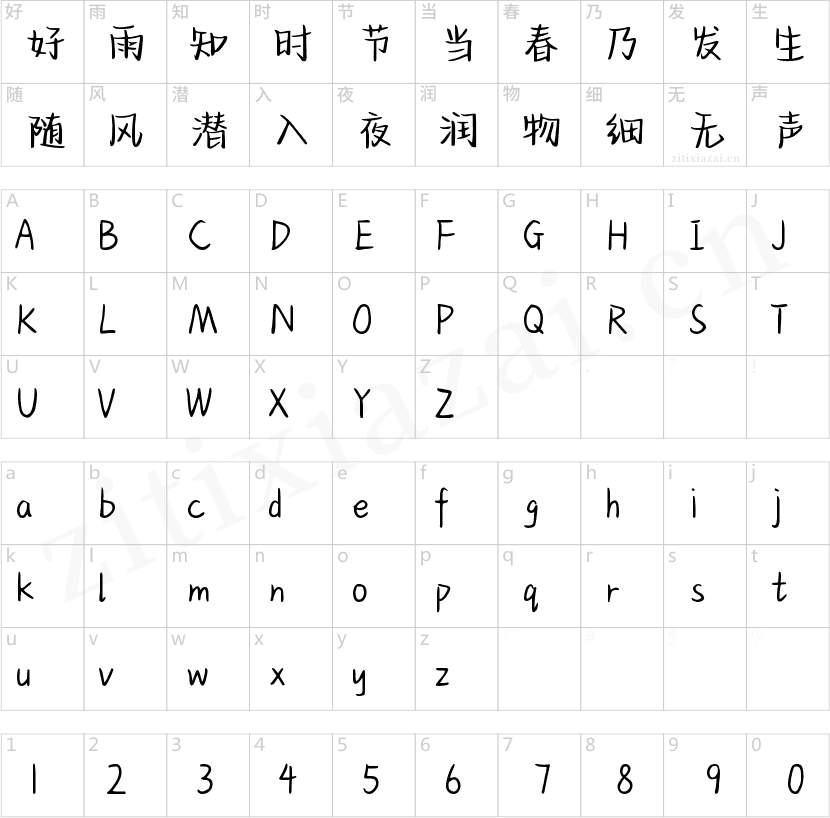
Aa他的例外不是你
Aa他的例外不是你字体
Aa他的例外不是你是一款非常具有艺术性的字体,它的设计灵感来源于对古典艺术的研究,同时又融入了现代字体设计的元素。字形优美,笔画粗细变化自然,给人以大气、典雅的感觉。Aa他的例外不是你是一款既传统又现代的字体,它的设计充满艺术感,美观大方,实用性也非常强。无论是对于设计师还是对于普通读者来说,都是一种非常不错的字体选择。Aa他的例外不是你适合用于具有艺术感的场合,比如海报、宣传单张、书籍封面等。由于其字形流畅且具有动态感,也适合用于大量的文本排版,如报纸、杂志等。